قبل أن يخرج أيُّ مُنتجٍ إلى النُّور، يمرّ برحلة طويلة من تخطيط، وتجريب، وبناء، ومراجعات… وهلمَّ جرًّا. والخطُّ منتج يُصَمَّم، على سبيل الاختصار الشَّديد، عبر ثلاث مراحل: التَّخطيط، فالتَّصميم، ثم التَّقديم. أمّا الجمهور فعادةً ما يتعرَّف على الخطِّ بترتيبٍ معكوس؛ يلتقي أولًا بصورة الخطِّ مُكتملةً في وسائط تعرضه في سياقاتٍ مختلفة، ثمَّ يلاحظ رسم الحروف وتفاصيل أشكالها، وقد يقوده فضوله بعد ذلك إلى أن يستكشف جذور الفكرة والقصَّة وراء نشأة الخطِّ.
أعني بـ«التَّقديم» تصميم الصُّور والوسائط التي يُعرَض من خلالها المنتج للجمهور. وفي حديثنا عن الخطِّ الطِّباعيِّ كمنتج، فإنَّ التَّقديم بطبيعته قائمٌ على نصوص تُكتَب به، لأنَّ الحرف يُعرَض من خلال كلمات تحتويه. ولهذا فإن تصميم التَّقديم النَّاجح يتطلَّب اختيار نصوصٍ منسَّقة نُلبِس عليها الخطَّ ليظهر في أفضل صورة ممكنة.
إن كان هدف التَّقديم يقتصر على استعراض أشكال الحروف ولا يتعدَّاه، فيمكننا أن نلجأ ببساطة إلى عبارات تُستخدم لهذا الغرض تحديدًا، مثل جُمل «البانغرام». و«البانغرام» عبارة تحتوي على جميع حروف اللُّغة مرَّة واحدة على الأقلِّ، وتُستخدم كأداةٍ لاختبار الخطِّ عند تصميمه، ولعرضه بعد إطلاقه. ولعلَّ من أشهر هذه العبارات في اللُّغة العربيَّة جملة الأبجديِّة: «أبجد هوَّز حطِّي كلمن سعفص قرشت ثخذ ضظغ».
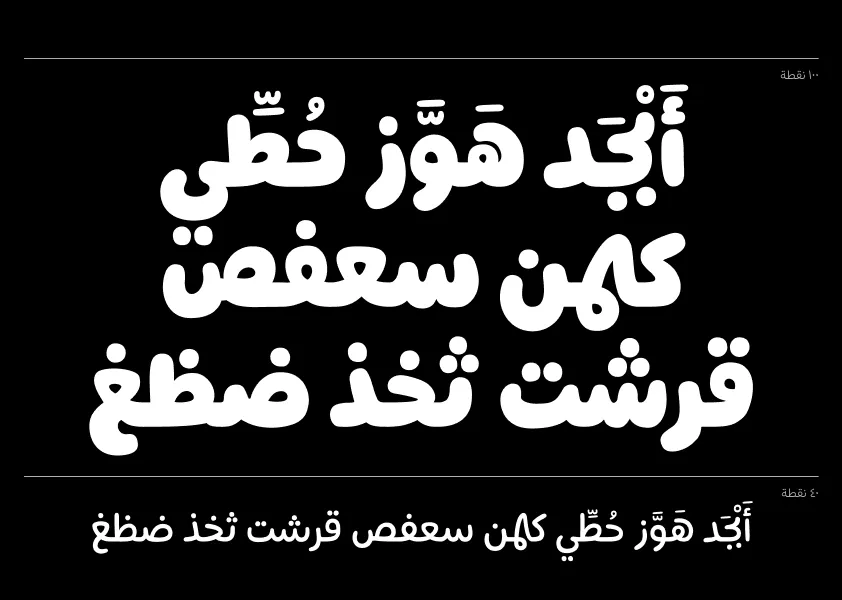
ومع أنَّ عباراتٍ كـ «البانغرام» ترسم لنا انطباعًا أوليًّا عن شكل الخطِّ وخامته البصريَّة، إلَّا أنَّها كلمات مجرَّدة من السِّياق، والسِّياق يكشف لنا سلوك الخطِّ في استخداماته الفعليِّة. غالبًا يُستحسن أن ننتقي كلماتٍ مُوزَّعة حروفها بتنويعة مألوفة لدى عين القارئ، مثل نصوص تشبه ما نقرأه في حياتنا اليوميَّة. فيمكن أن نستخدم «بانغرامًا» يجمع الحروف ويُظهر تنويع الحروف في نفس الوقت مثل عبارة: «نصّ حكيم له سرّ قاطع وذو شأن عظيم مكتوب على ثوب أخضر ومغلَّف بجلد أزرق» وغيرها.
النُّصوص كلمات، والكلمات معانٍ، والمعاني فرصة لأن نسرد قصَّة الخطِّ بما يشكِّل هويته كمنتج فنِّي بعيدًا عن النُّصوص الجامدة.
حين يحمل النَّص فكرة، يشارك الخطَّ في نقل المحتوى إلى المتلقِّي. ولمّا وجدتُ أن النُّصوص ذات المعاني تُنصِف الحروف أكثر من الجمل الاختباريَّة المجرَّدة، تطرَّقت إلى استخدام الشِّعر العربيِّ؛ ففي القصيدة كلُّ كلمةٍ مُختارة بدقَّة، وكلُّ صُورة بلاغيَّة من استعارة وتشبيه وغيره تزيد الكلمات جمالًا.
والشعر بطبيعته يُقرأ ليُتذوَّق؛ على خلاف النصِّ العاديِّ الذي يُقرأ لينقل معنًى وظيفيًّا. يفرض الإيقاع لحظة تأمُّل تسمح للقارئ بأن يرى الحروف قبل أن يقرأ الكلمات. فالإيقاع يخفِّف سرعة القراءة، واللُّغة الموزونة تجذب الانتباه إلى بناء الكلمات البصريِّ.
كما أنَّ قصائد اللُّغة العربيَّة جزءٌ من ذاكرةٍ ثقافيَّةٍ مشتركة، ومخزونٌ من الصُّور والمشاعر الَّتي يكتنزها القارئ. والخطُّ عندما يُقدَّم من خلال لغة مشتركة، يختصر المسافة بينه وبين المتلقِّي.
أصبحتُ أجمع القصائد بعين المصمِّم؛ فإمَّا تلفتني أبيات شعرٍ بمعانيها، أو بتشكيلتها اللُّغويَّة، أو بتركيزها على حروف وتراكيب معيَّنة. مثلًا قد أركِّز على تنوُّع الحروف تارة لأعرض الخطَّ بشكلٍ عام، أو قد أُفضِّل تارة أبياتًا تركِّز على حروف معيَّنة كالميم النهائيَّة فأختار قصيدة ميميَّة مثلًا. أجمع قصائد كثيفة التَّشكيل، وأخرى كلماتها متوازنة الطُّول، وأخرى غنيَّة بالتَّنقيط والهمزات مثلًا. أستخدم التباين بين الأوزان لإبراز كلمات معيَّنة، أو أضيف أحيانًا رسومات بسيطة تكمل جمال الحروف.
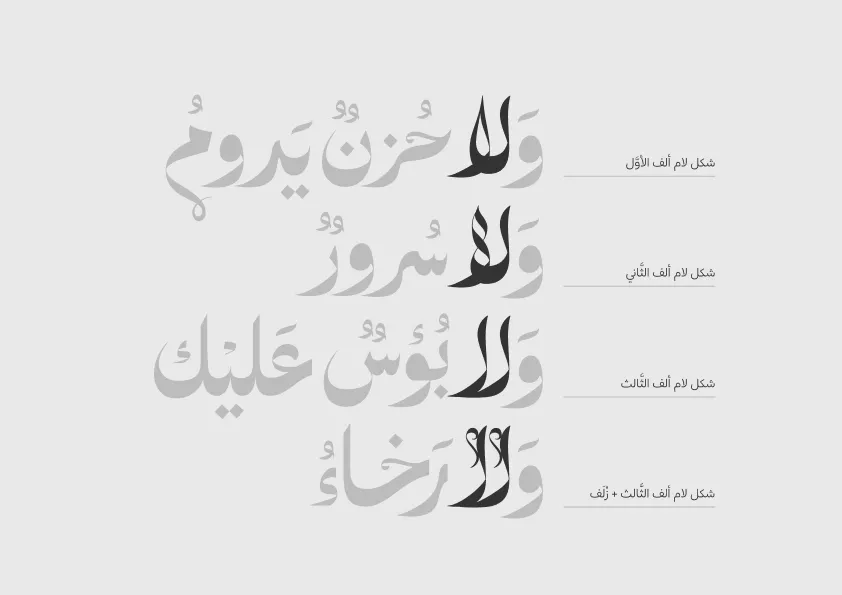
وليس حضور الشِّعر مقتصرًا على مرحلة التَّقديم فقط؛ فأحيانًا أخربش أفكارًا عشوائيَّة لحروف من نصوص يتحوَّل بعضها إلى بذرة لخطٍّ جديد. كثيرًا ما أنطلق من نصٍّ كبيت شعر حضر مؤخَّرًا في ذهني؛ فأستعير من معانيه دلالات بصريَّة أرسمها، فيقود المعنى شكل الحرف، ويرتِّب علاقات الحروف بين بعضها ويتَّجه بي إلى مسارات جديدة في التَّخطيط. فقد يحضر الشِّعر في عمليَّة التَّصميم منذ مراحل الاستلهام مبكِّرًا، أو كنصوص اختباريَّة للخطِّ عند تطويره، وأخيرًا عند العرض كما تطرَّقت إليه هنا.